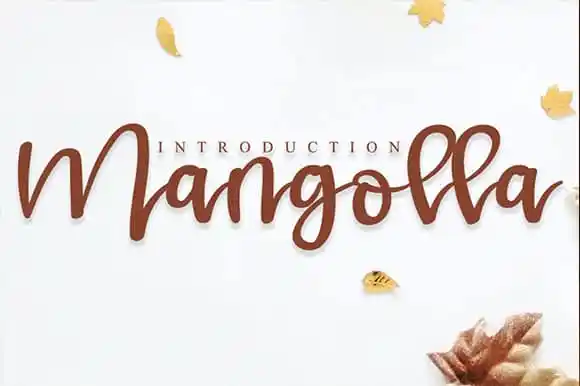
Mangolla Script Font – Fonte Grátis
Mangolla Script Font
A Mangolla Script Font é uma escolha perfeita para quem busca adicionar um toque autêntico a projetos digitais e impressos. Com seu estilo elegante e fluido, essa fonte é ideal para criações que exigem um ar de sofisticação e criatividade. Seja você criando cartões de apresentação com uma pitada de personalização ou desenvolvendo logos para suas redes sociais, a Mangolla Script Font será o companheiro perfeito. Suas linhas suaves e rústicas combinam muito bem em projetos como embalagens de produto, revistas digitais e até mesmo em fotografias ou posters com um estilo vintage que se tornarão verdadeiros destaques. Em uma época onde tudo está buscando a identidade visual perfeita, essa fonte pode ser o elemento especial que dá seu projeto aquele toque definitivo e único.